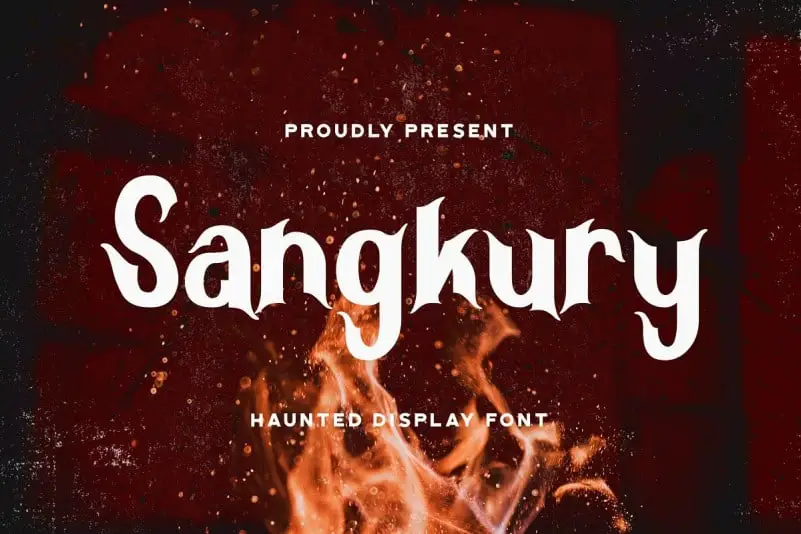
A Sangkury Display Font é uma seleção de tipos de exibição criados para quem busca algo único e poderoso no design do horror. Este pacote inclui uma opção de distorção que cria um efeito de fogo, tornando-a perfeita para qualquer projeto que precise de uma sensação sombria. Com todas as letras em maiúsculas, mas oferecendo estilos únicos tanto para letras maiúsculas quanto minúsculas, ela combina a versatilidade do tipo clássico com um toque surpreendente e original. Ideal para arquitetura de horror, como filmes de terror, vestuário escuro ou qualquer outro design que exija uma atmosfera sombria e assustadora. A Sangkury Display Font também se destaca por sua aparente simplicidade e humor gráfico, tornando-a perfeita para arquitetura de espíritos, festas de Halloween ou outras ocasiões sinistras. Seu design dinâmico e atraente combina coragem suficiente para ser usado em tipografias de exibição, garantindo que sua mensagem seja notada e lembrada nas superfícies mais visíveis. Não apenas um tipo de horror, mas uma fonte incrivelmente versátil que irá enriquecer seu trabalho design gráfico com personalidade e estilo.